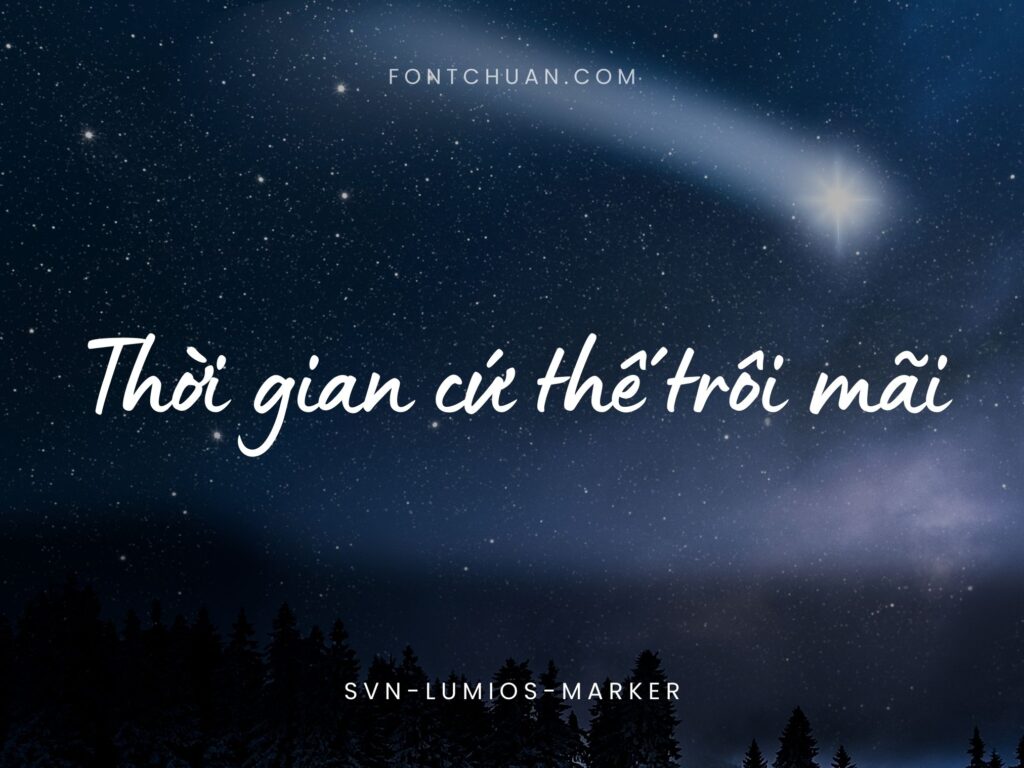
Font SVN Lumios Marker Việt Hóa
Tác giả Font: Elena Genova
Font SVN Lumios Marker là phiên bản Việt hóa của kiểu chữ Lumios Marker, được thực hiện bởi STYLEno.1 Fonts. Lumios Marker là một kiểu chữ viết tay tự do, được tạo ra bằng bút Pilot Sign Pen, mang đến cảm giác tự nhiên và thân thiện. Font này hỗ trợ cả các ký tự Latin mở rộng và Cyrillic cơ bản, được tăng cường với nhiều ligature và ký tự thay thế, giúp tạo nên sự đa dạng và linh hoạt trong thiết kế. Ngoài ra, Lumios Marker còn đi kèm với một bộ font các yếu tố thiết kế, hữu ích trong việc tạo thương hiệu, thiệp chúc mừng và các dự án sáng tạo khác. Font này phù hợp cho nhiều mục đích sử dụng như thiết kế logo, tiêu đề, bao bì sản phẩm và các ấn phẩm truyền thông.
SVN Lumios Marker lý tưởng cho các dự án thiết kế yêu cầu sự tự nhiên và thân thiện, như thiết kế logo, tiêu đề, bao bì sản phẩm và các ấn phẩm truyền thông. Đồng thời, font này cũng có thể được sử dụng như một Font chữ ẩm thực, giúp các nhà hàng, quán ăn và thương hiệu thực phẩm tạo ra sự gần gũi, ấm áp và thu hút trên menu, bao bì sản phẩm hoặc các ấn phẩm quảng cáo. Ngoài ra, Lumios Marker vẫn phù hợp với các ngành giáo dục, thiệp cưới, cũng như các sự kiện như Tết, Giáng sinh, Halloween và các lễ hội khác.